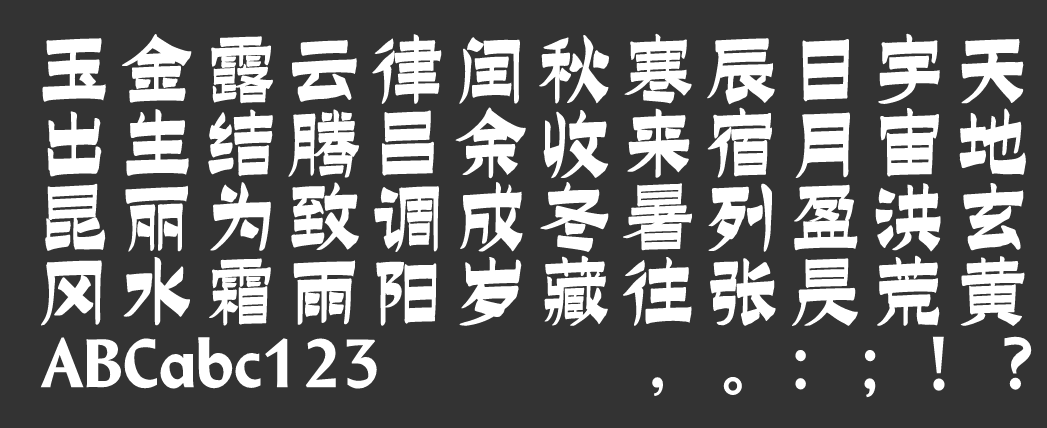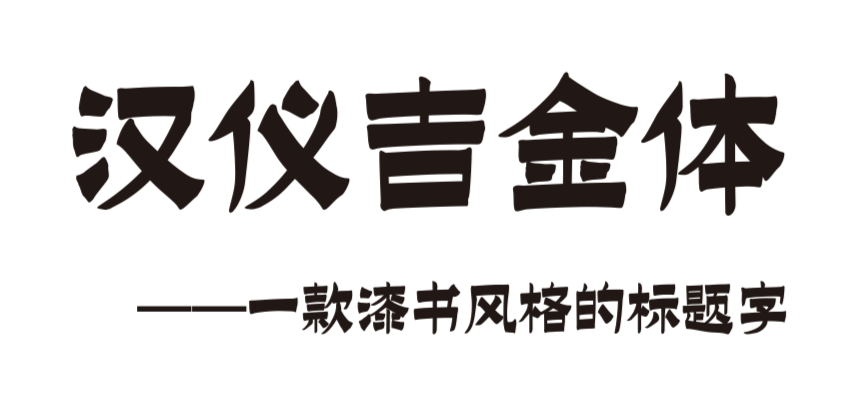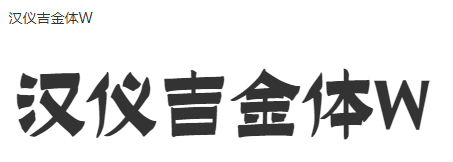
汉仪吉金体 | 背景介绍
“汉仪吉金体” 是由设计师郑建,倾心创作的一款漆书风格的标题字。该字体在传统漆书的基础上融入了美术字的书写意味,使其在现代的应用环境中有更好的适用性。
设计师以清代书画家、扬州八怪之首——“金农”书写的漆书为创作蓝本,并运用现代工具,保留性地再现了这位野逸文人,潇洒自如的创作心境。使得今日让勇于突破书法法度的漆书,重新走近我们的视野。
汉仪吉金体 | 结构特点
字面大而中宫放松,使字体的正负形空间比例恰当,字形清晰易读。
汉仪吉金体 | 笔画特点
字体沉厚朴实,横粗竖细。横画粗且间距密,像笔刷横刷而过,竖画则细而有力。粗细之间形成强烈的反差,突破了传统书法的书写法度。
字体棱角分明、笔划方正、只“折”不转,展现着创作者的用笔率真和随心所欲的创作心境。
笔画遒劲钝拙、古拙严谨,在横平竖直的书写中融入了曲线设计,为字体增添了生动的气息。
以笔为刀,两端整齐。在保留了隶书结构的基础上,削弱了蚕头雁尾的古味,使字体的块面感和装饰感更强。
汉仪吉金体 | 异体字
汉仪吉金体 | 西文字母
西文字母参考并借鉴了中文笔画的粗细关系,使中西文组合搭配和谐统一。
汉仪吉金体 | 排版效果
字体排版规范整齐。相比金农的作品《漆书相鹤经轴》而言,减弱了字体穿插组合中的画面效果,使其更适应现代多样化的排版方式。